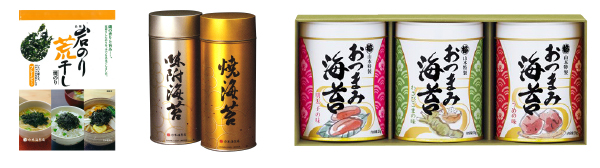
Perfume label 香水ラベル
日本語の気水は、健康な美肌のために三香堂で開発された
ヨーロッパ限定商品の神秘ローションです。
Drink label 飲料ラベル
クオリティの高いお酒であれば文字の主張も控めの方がおしゃれです。
ごまふわわ
じっくりと焙煎して丁寧にすった白ごまを使用したほんのり甘い味わいのごま焼酎。特に女性をターゲットにした丸みのあるかわいらしさを強調しました。
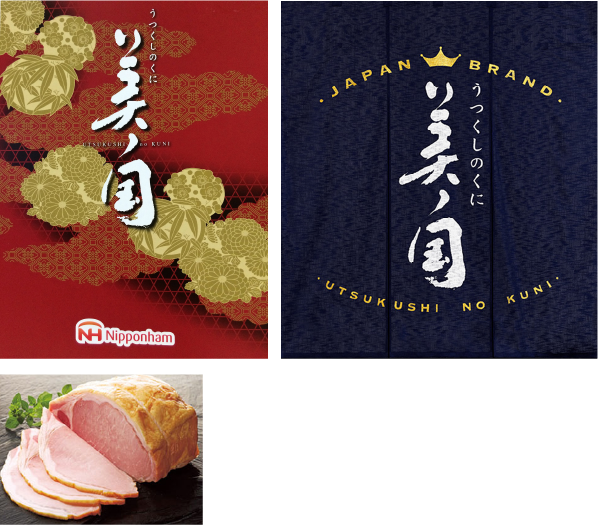
Other foods design その他食品
商品の顔ともいうべきラベルは文字によってこれほどまでに表情を変えます。
ニッポンハム
国産プレミアム「美ノ国」(うつくしのくに)
2006年自社農場で育てた豚から最高においしいハムを作りたい、そんな思いで「美ノ国」は生まれました。
食品ロゴのイメージとして、特に美の特徴を、いかに表現し、印象を与えるかがポイントで、読みやすく存在感を合せ持った文字が、要求されました。
山本海苔
全国加工海苔品評会で農林水産大臣賞受賞したおつまみ海苔うめ味のパッケージをリニューアルしました。
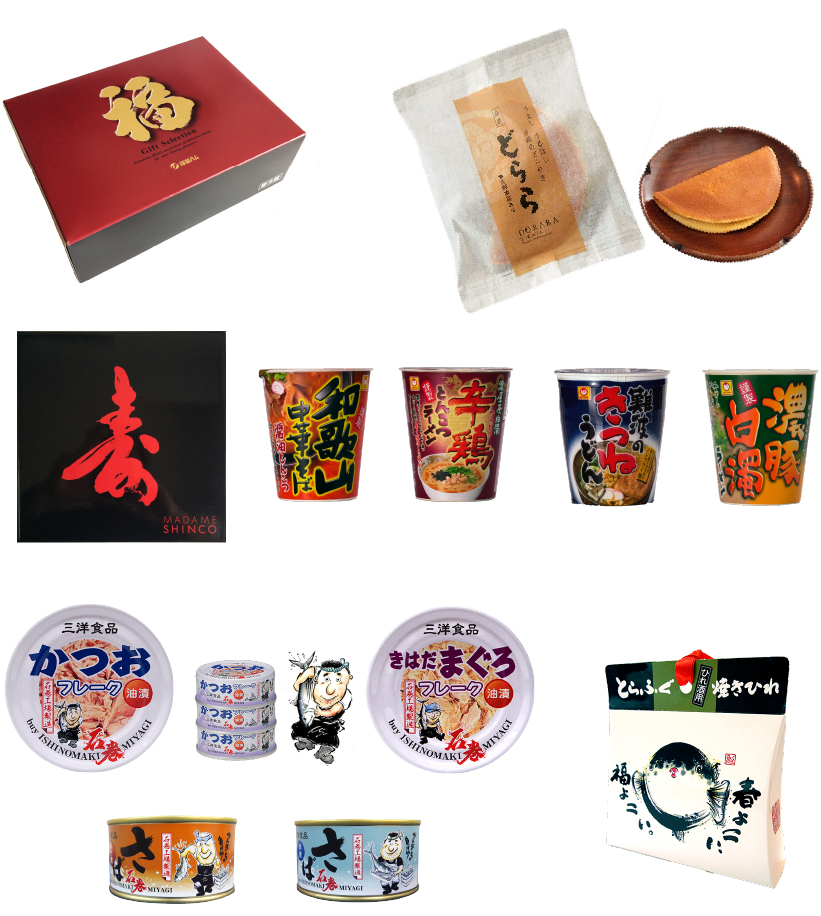
どらら
吉野本葛と米粉、そして山芋の組み合せで、もっちりした食感としっとりした口当たりが絶品のどら焼き。普通より一回り小さい、ぽってりとした形を筆で表現しました。
福留ハム
Gift selection